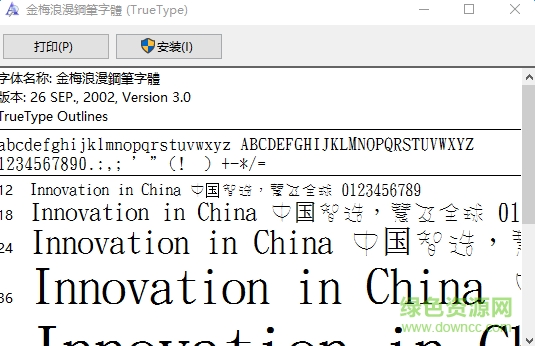
金梅浪漫鋼筆字體是金梅字庫中很有個(gè)性的一款字體,就像它的名字所寫一樣是一款比較浪漫的鋼筆字體,所以寫出來的字是很細(xì)的,可以用于寫作創(chuàng)作方面,歡迎有需要的朋友來綠色資源網(wǎng)下載。
金梅浪漫鋼筆字體確實(shí)是一款很不錯(cuò)的電腦字體,可以用在很多方面,主要是因?yàn)閷懗鰜淼淖质呛芎每吹?,所以大家也很喜歡用這款字體。